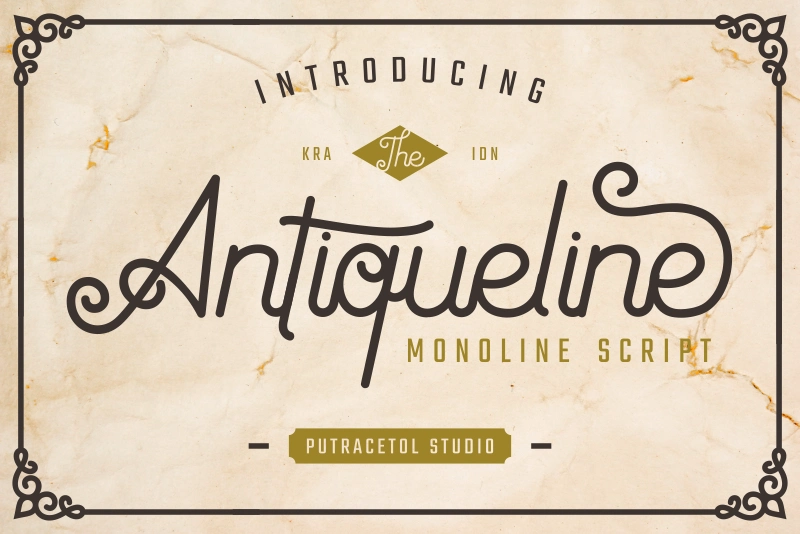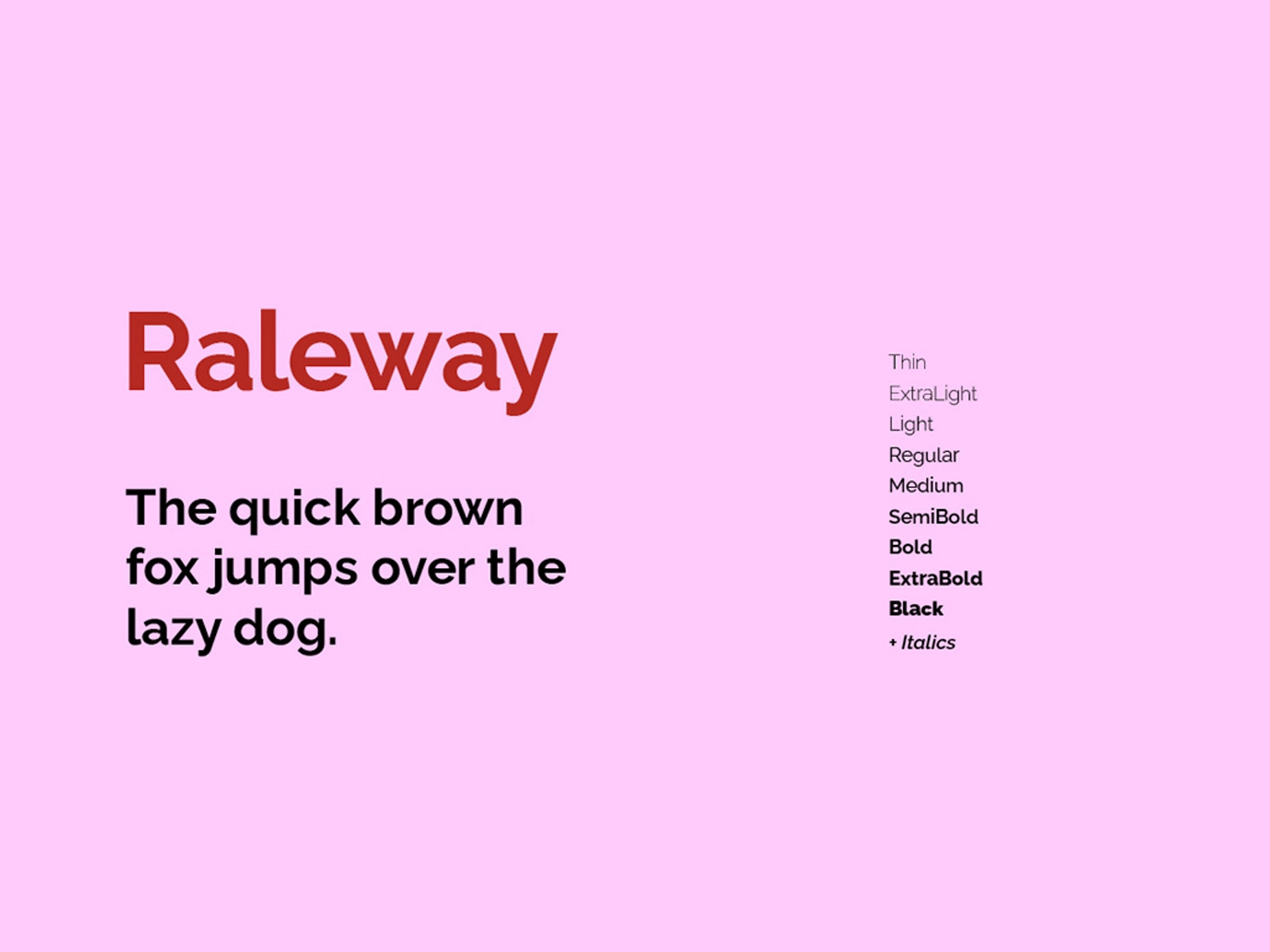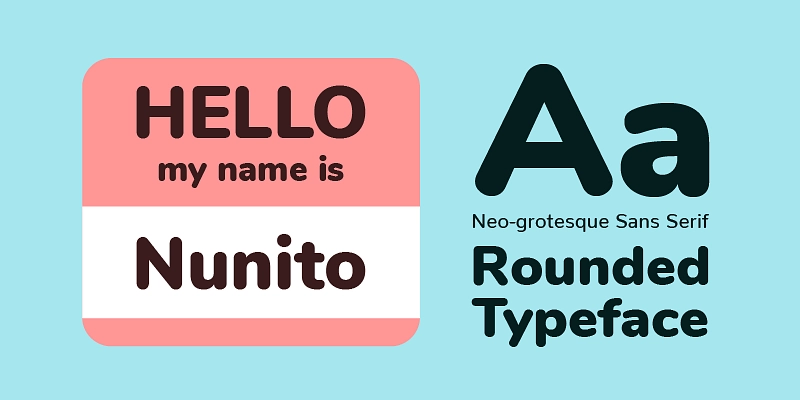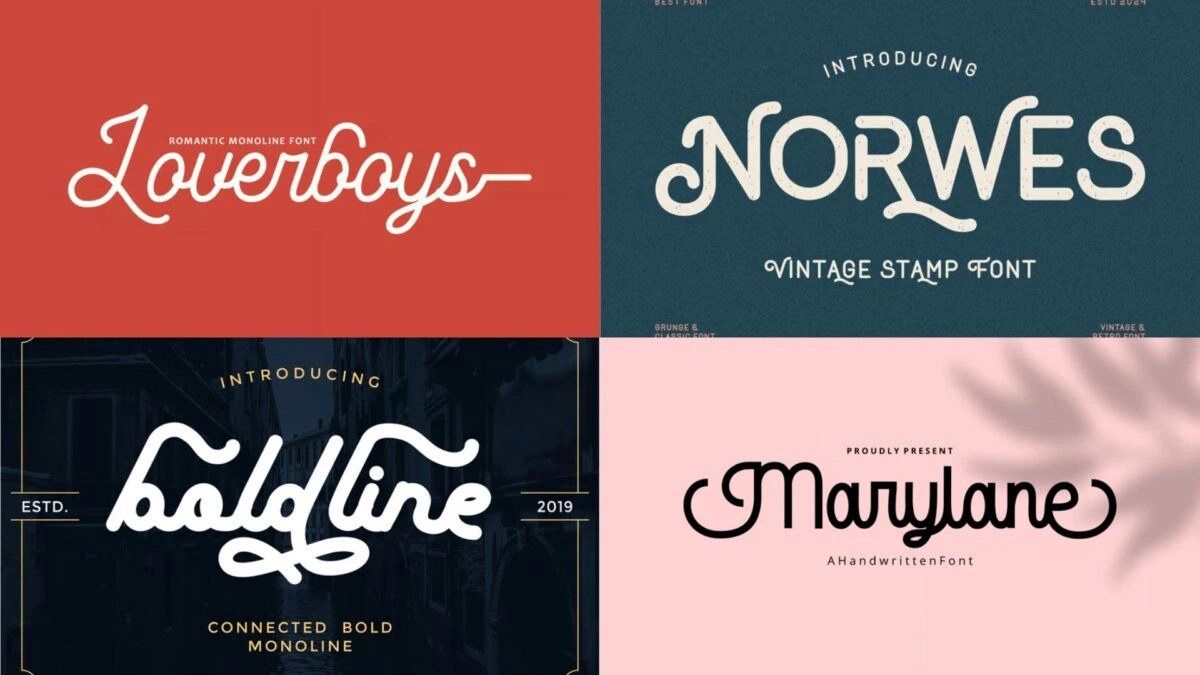
Монолинейные шрифты
Введение
В 2025 году монолинейные шрифты уверенно занимают заметное место в брендинге, веб-дизайне и печатных материалах. Их главный визуальный принцип прост и ясен: все элементы букв имеют одинаковую толщину линий. Именно эта равномерность придает тексту ощущение гармонии, современности и утонченности.
Монолинейные гарнитуры сочетают в себе минимализм и универсальность: они одинаково хорошо смотрятся на экранах и в печатной среде, создавая впечатление стиля вне времени. Благодаря чистоте форм такие шрифты могут быть как нейтральной основой, так и акцентным инструментом для смелых дизайнерских решений.
Что такое монолинейные шрифты
Монолинейными называются шрифты, в которых все линии букв имеют одинаковую толщину. В отличие от традиционных гарнитур с переменной толщиной штрихов, здесь каждый элемент буквы выглядит равномерным и сбалансированным. Они часто используются в логотипах, айдентике, интерфейсах и печатной продукции.
Монолинейные шрифты придают тексту минималистичный и элегантный облик, повышают читаемость и легко адаптируются к разным задачам. Наиболее часто они встречаются в виде скриптовых или гротескных (sans-serif) решений, а их универсальность позволяет им органично сочетать простоту и утонченность. Дизайнеры ценят их за способность добавлять проекту изысканность и легкость.
Появление монолинейных шрифтов связано с началом XX века, когда широкое распространение получили пишущие машинки. Техническая необходимость создавать буквы с одинаковой толщиной линий постепенно переросла в эстетический прием. Многие ранние шрифты этого типа разрабатывались по образцу чистых линий рукописного письма и архитектурных чертежей.
С развитием цифровых технологий монолинейные шрифты получили новое дыхание. Компьютерная типографика открыла путь к разнообразным интерпретациям и экспериментам: от классических решений до современных вариаций с необычной пластикой. Сегодня они существуют в широком спектре стилей, позволяя дизайнерам подбирать наиболее подходящее решение под разные проекты. Их эволюция продолжается, формируя новые визуальные возможности в графическом дизайне.
Преимущества монолинейных шрифтов
Ключевая особенность монолинейные шрифтов – это равномерная толщина линий, что делает текст цельным, аккуратным и современным. Благодаря этому они завоевали популярность в дизайне, где ценятся чистота форм, минимализм и универсальность.
Чистота и минимализм
Отсутствие перепадов толщины штрихов придает буквам ясность и завершенность. Такая сдержанность соответствует философии «меньше – лучше», позволяя тексту выглядеть продуманным и лаконичным. Минимализм монолинейных шрифтов делает их идеальными для современного визуального языка, где важна простота восприятия.
‍Гармония и баланс
Единая толщина линий создает ощущение визуального равновесия. В отличие от традиционных шрифтов с контрастными штрихами, здесь каждая буква кажется тщательно выверенной. Такой подход усиливает ощущение профессионализма и доверия, что особенно важно в брендинге и фирменном стиле.
Геометрическая точность
Многие монолинейные гарнитуры строятся на основе геометрических принципов: ровные линии, правильные круги, выверенные углы. Это придает буквам современную эстетику, которая одинаково хорошо работает как в строгих корпоративных проектах, так и в декоративных решениях.
Читаемость и ясность
Одним из главных достоинств монолинейных шрифтов является их высокая читаемость. Равномерность штрихов помогает легко различать буквы даже в мелком кегле или на цифровых экранах.
Универсальность в дизайне
Монолинейные шрифты отлично вписываются в проекты разных стилей – от современных минималистичных до классических изысканных. Они одинаково органично смотрятся на свадебных приглашениях, постерах, логотипах и в социальных сетях. Дополнительные наборы символов и мультиязычная поддержка еще больше расширяют их возможности.
Популярные монолинейные шрифты
Скриптовые монолинейные шрифты
Скриптовые гарнитуры создают эффект рукописного текста, добавляя теплоту и индивидуальность.
Antiqueline – изящный винтажный скрипт с богатым набором лигатур, идеально подходит для ретро-дизайнов и декоративных проектов.
Pacifico – дружелюбный и неформальный скрипт, часто используемый в веб-дизайне и на упаковке.
Lobster – динамичный и узнаваемый шрифт, который хорошо работает в логотипах и заголовках.
Гротескные монолинейные шрифты
Гротески подчеркивают современный, минималистичный стиль и высокую читаемость.
Rambors – строгий all-caps шрифт, который идеально подходит для логотипов и заголовков.
Raleway – элегантный и легкий гротеск, часто используемый в интерфейсах и на сайтах.
Nunito – сбалансированный округлый sans, который отлично смотрится в приложениях и цифровых сервисах.
Где использовать монолинейные шрифты
Благодаря своей чистоте, аккуратности и универсальности монолинейные шрифты нашли применение в самых разных сферах дизайна. Их равномерный штрих и геометричность позволяют гармонично вписываться в проекты как с минималистичной эстетикой, так и с декоративным уклоном.
Заключение
Монолинейные шрифты отражают ценности современного дизайна: ясность, простоту и внимание к деталям. Их равномерная толщина штрихов создает ощущение порядка и точности, а в то же время придает тексту легкость и элегантность. Монолинейная типографика универсальна – она одинаково уверенно работает и в цифровых интерфейсах, и в фирменной айдентике, и в печатных проектах.